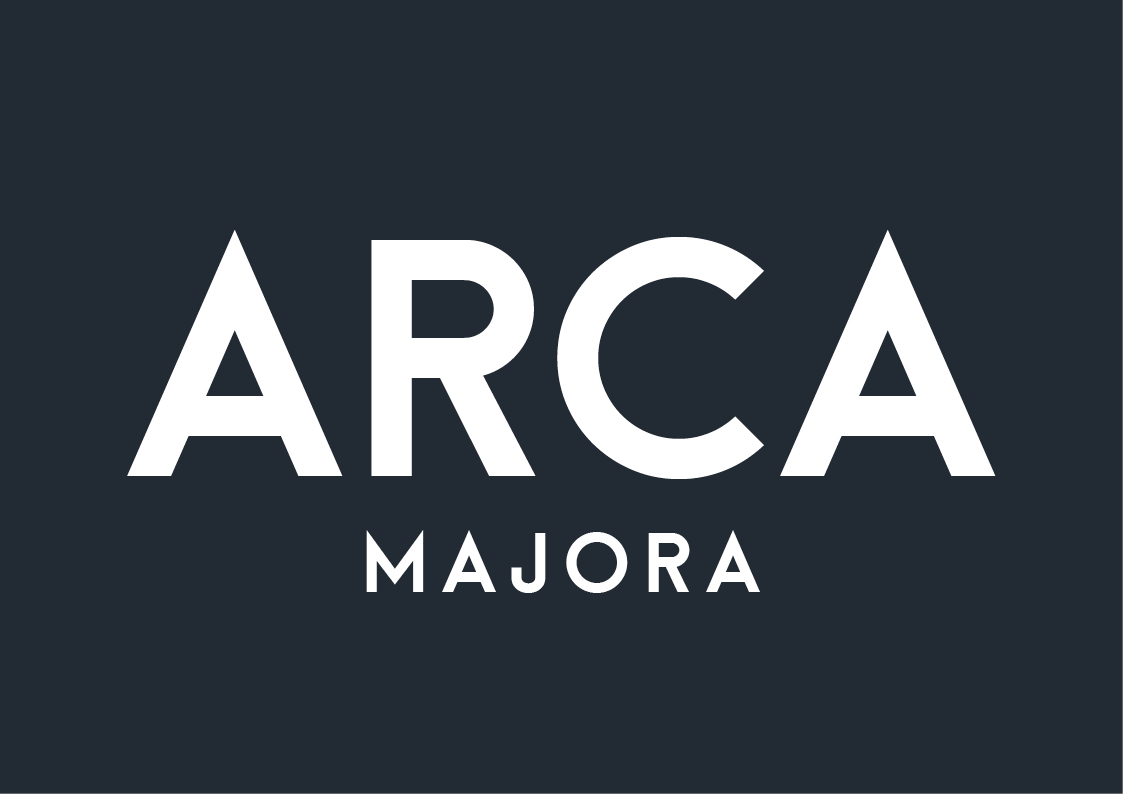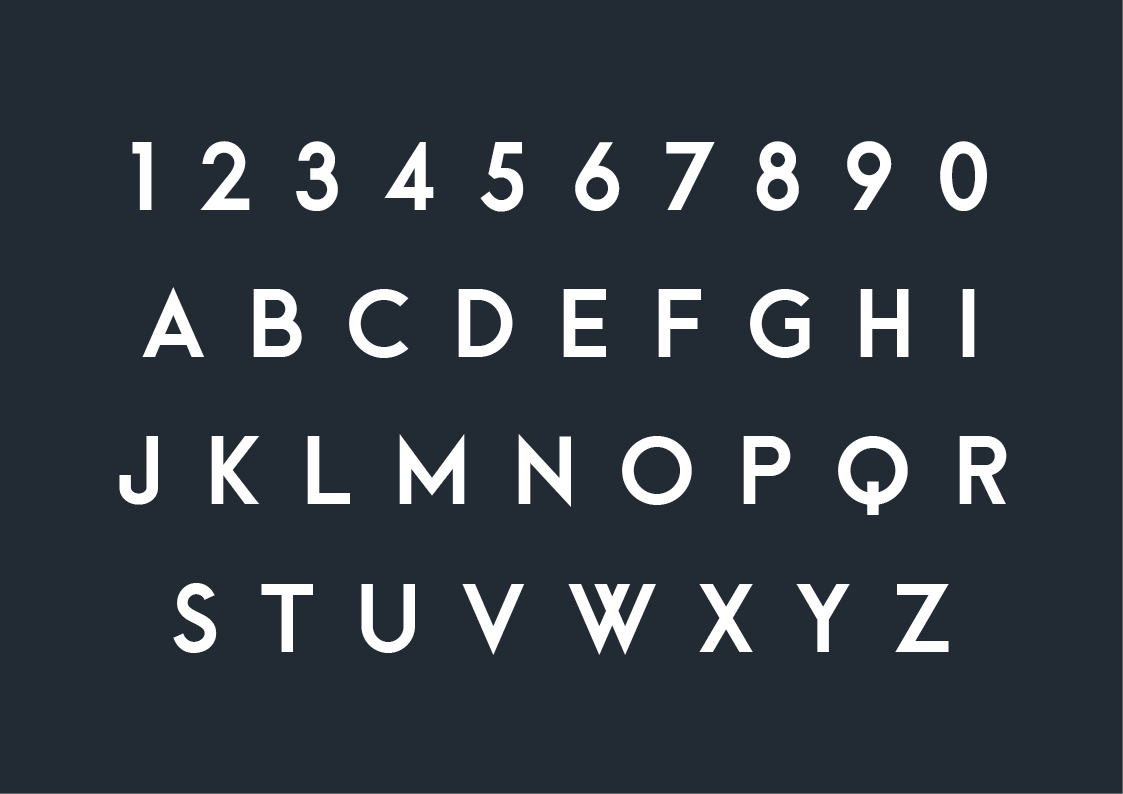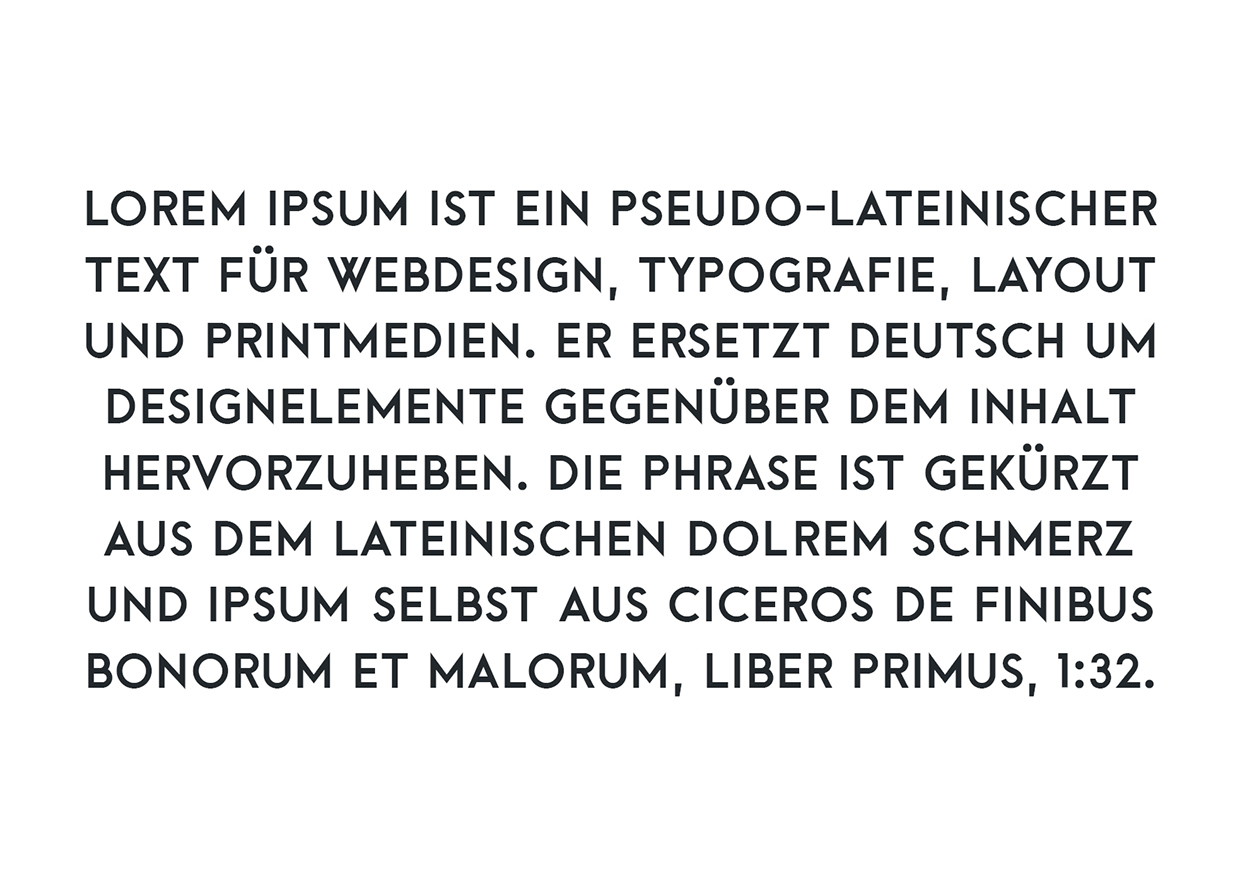
En la edición de hoy de monday font, os presentamos ARCA, una bonita fuente tipográfica para descargar gratuitamente sans-serif y mayúsculas. Creada por el diseñador dubaití Alfredo Marco Pradil.